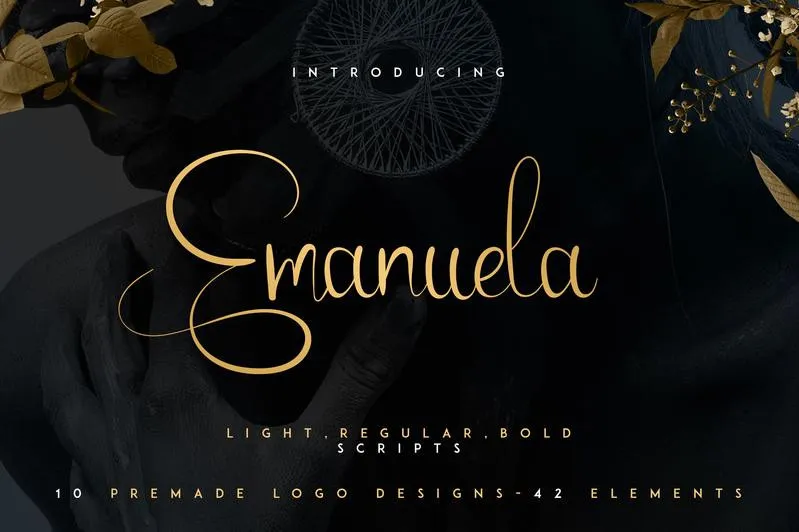
Emanuela Typeface – Download Grátis
Introduzimos a Emanuela Typeface, uma elegante tipografia feita à mão que transmite um charme pessoal. Com linhas ressaltadas e finas, esta fonte é perfeita para projetos de marca, designs para casa ou embalagens de produto. Seja por ela usada como overlay estilizado sobre qualquer imagem de fundo, a Emanuela traz uma personalidade única que complementa perfeitamente qualquer projeto visual. Agradável e funcional, esta fonte é ideal tanto para designers iniciantes quanto para profissionais experientes em busca de um toque distintivo. Descubra como Emanuela pode dar novo vida à sua arte digitizada.